2023 年 15 种最佳黑客字体(免费和付费)
已发表: 2023-08-05您是否曾经努力为您的图形设计项目寻找完美的字体? 您是否厌倦了使用其他人都在使用的旧字体?
好吧,别再看了! 在这篇博文中,我们将介绍 15 种最佳黑客字体,它们将改变您的设计并将其提升到一个新的水平。
在当今的数字时代,字体在使您的设计脱颖而出方面发挥着至关重要的作用。 由于有大量可用选项,为您的项目选择正确的字体可能会让人不知所措。
这就是为什么我们整理了 15 种最佳黑客字体的列表,它们一定会激发您的创造力并增强整体设计美感。
无论您是设计徽标、网站、海报还是任何其他图形项目,正确的字体都可以发挥重要作用。 这些黑客字体是根据其独特性、多功能性以及为您的设计增添额外专业性和创新性的能力而精心挑选的。
因此,坐下来,放松一下,准备好发现将彻底改变您的创作过程的字体!
最佳高级黑客字体
希望将您的平面设计项目提升到一个新的水平? 别再犹豫了! 在本文部分中,我们将介绍最好的优质 Hack 字体,保证为您的设计增添现代和时尚的触感。
那么,为什么不花点时间看看这些令人难以置信的字体并立即升级您的设计游戏呢?
黑客生活
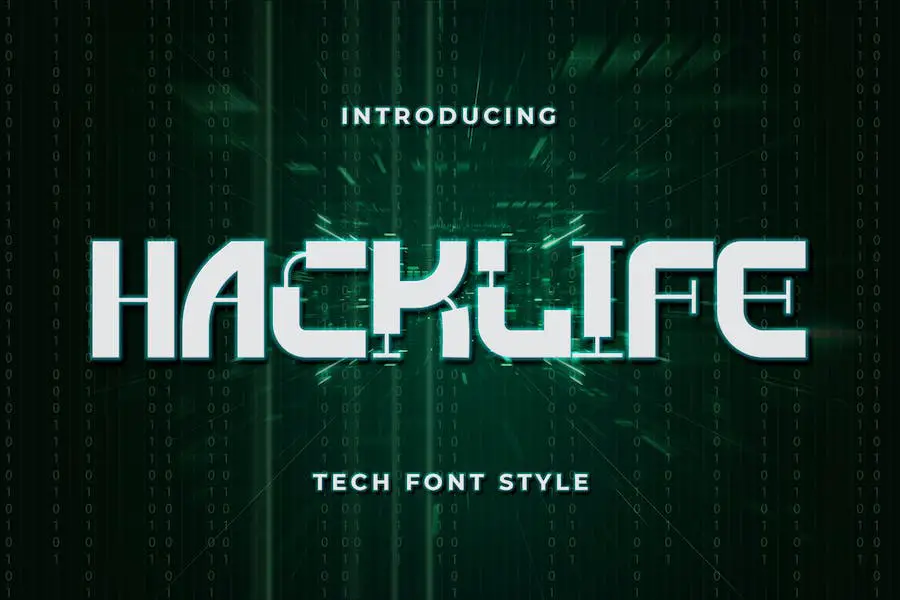
Hacklife 是一种独特而前卫的字体,可以提升您的设计项目。 这种受科技启发的字体具有未来感,非常适合任何科技或计算机主题的设计。 凭借其时尚和现代的外观,Hacklife 将把您的设计提升到一个新的水平。
无论您是在制作网站、徽标,甚至是纹身设计,这种字体都会增添一丝精致和风格。
因此,如果您是一名图形设计师,正在寻找一种字体来增强您的项目,那么 Hacklife 绝对值得考虑。 使用这种未来派字体为您的设计增添额外的优势。
黑客机器人
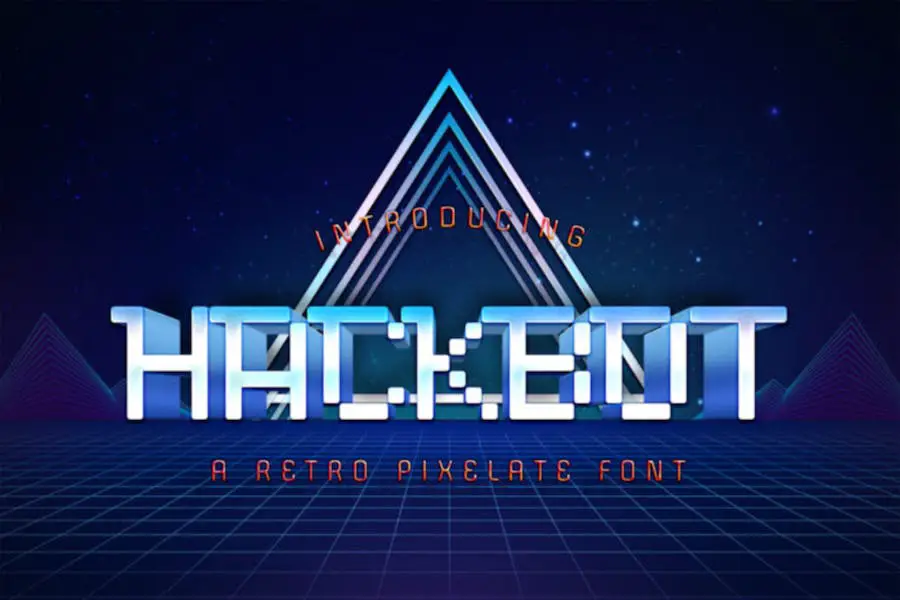
Hackbot 是一种复古风格的字体,可为您的设计增添一丝怀旧气息。 凭借其独特、有趣的字母和复古的感觉,它可以让你回到旧时代。
这种字体采用无衬线书写风格,但具有复古设计风格,使其真正成为独一无二的字体。 无论您是要推广游戏、创建报价单还是进行复古设计,Hackbot 都能完美满足您的所有需求。
Hackbot 的魅力在于字母之间的间隙,这赋予它真正的复古氛围。 这是一种脱颖而出的字体,捕捉了过去的精髓,同时仍然具有视觉吸引力和吸引力。
每封信都经过精心制作,为您的项目带来奇思妙想和有趣的感觉,使它们真正迷人。
Hackbot 是一种多功能字体,可用于多种应用程序,非常适合游戏开发人员和图形设计师。
无论您是想创建引人注目的海报、设计令人难忘的徽标,还是为社交媒体帖子添加复古风格,这款字体都能满足您的需求。 是时候释放您的创造力并让 Hackbot 来说话了。
格斗王
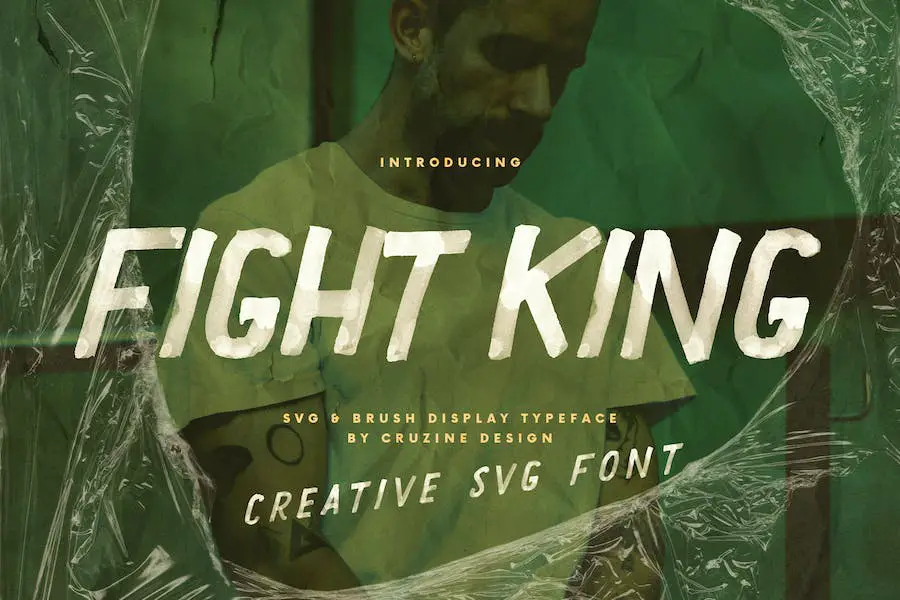
Fight King 是一种独特的手写黑客字体,可为您的项目带来画笔、粗糙或垃圾风格。 这款无衬线显示字体采用大胆的水彩标记设计,非常适合为任何设计增添都市艺术气息。
无论您是在从事垃圾摇滚风格的项目,还是想让您的设计具有前卫的外观,Fight King 都是适合您的字体。 其手工制作的感觉和强烈、大胆的笔触使其成为任何创意活动的杰出选择。
因此,如果您正在寻找一种多功能且引人注目的字体来让您的设计流行起来,请尝试一下《Fight King》。 它一定会给您的项目带来额外的风格和个性!
流畅的线条
隆重推出 Flowing Lines,这是一种手写黑客字体,可为您的项目添加画笔、粗糙或垃圾风格。 这种无衬线显示字体非常适合创建大胆且艺术的外观,特别是对于垃圾、城市或艺术项目。
凭借其大胆的标记风格笔触,Flowing Lines 为您的设计带来独特而前卫的氛围。
这种黑客字体用途广泛,可用于各种项目,从海报到徽标以及介于两者之间的所有内容。 其流畅的线条和手写的外观为任何设计增添了一丝真实性和创造力。
无论您正在从事复古风格的项目,还是希望为您的设计增添一丝叛逆气息,Flowing Lines 都能满足您的需求。
这种字体的画笔风格赋予它原始和有机的质感,使其从其他字体中脱颖而出。 它为您的设计增添了手工品质感,就好像每个字母都是精心手绘的。
Flowing Lines 的粗糙边缘和垃圾摇滚氛围为任何项目带来都市酷感,使其成为那些寻求非传统和叛逆美学的人的首选字体。
Flowing Lines 凭借其大胆的标记笔触,确保您的信息被清晰地看到和听到。 其强烈而自信的外观引人注目,非常适合在设计中使用标题或引人注目的文字。
糖
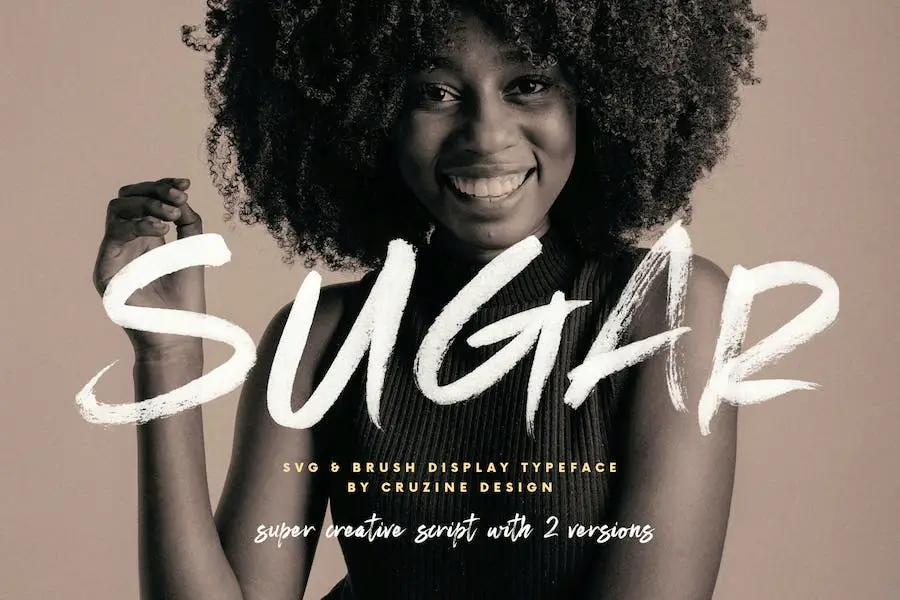
Sugar 是一种独特且多功能的字体,它将把您的设计项目提升到一个新的水平。 凭借其笔刷、粗糙或垃圾风格的脚本,它为任何作品增添了有机和手工制作的触感。
无论您是从事垃圾、城市还是艺术项目,这种手写黑客字体都是完美的选择。
Sugar 的独特之处在于它的笔刷起源,为您的设计带来原始和艺术的外观。 这就像使用真正的画笔来创建版式,但具有数字字体的便利性和精确性。
这种字体非常适合为您的设计添加质感和个性。 其粗犷和垃圾摇滚风格营造出一种前卫感和都市氛围,非常适合时尚、音乐或街头风格的项目。 它真正抓住了另类和叛逆的精神。
黑客
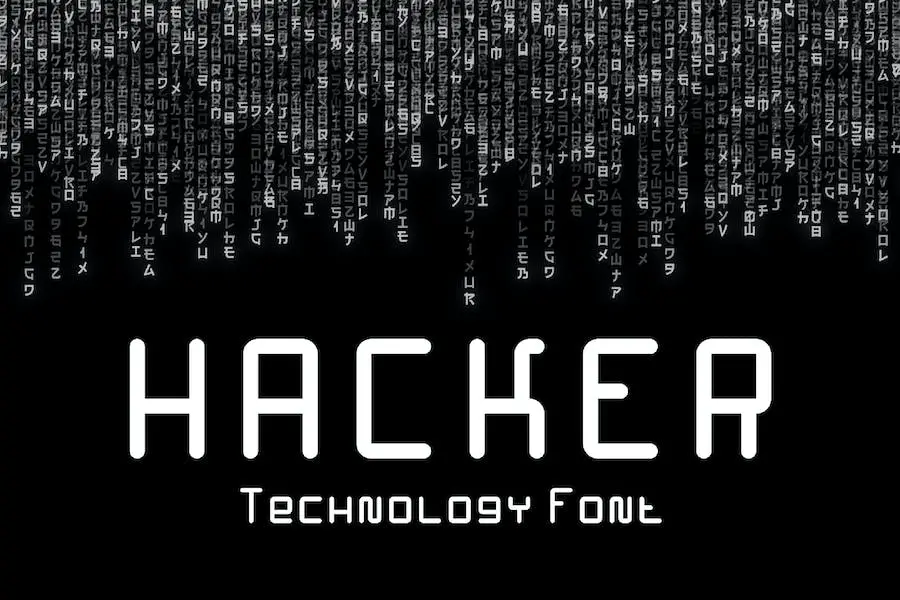
Hacker 是一款令人难以置信的圆形显示字体,散发着明显的复古魅力,让人想起 20 世纪 80 年代。 它毫不费力地抓住了改变世界的计算机革命的本质。
凭借其诱人而大胆的美学,《黑客》绝对是一种视觉享受。 其独特的吸引力使其非常适合各种项目,特别是与网络、安全、互联网、新技术、通信、编码、数据、电子、数学、网络、商业等相关的项目。
这种字体带有一种有趣的熟悉感,仿佛在低声诉说着过去的故事,同时又毫不费力地融入了现代设计景观。 其平滑的曲线和鲜明的特征使其成为任何需要怀旧气息的项目的完美选择。
无论您是创建网站、设计徽标还是制作海报,Hacker 都能增添真实感和个性感。 它毫不费力地捕捉了数字世界的本质及其对创新的不懈追求。
黑客的多功能性是无止境的。 它可以无缝适应任何环境,毫不费力地增强整体设计。 从时尚现代到古怪俏皮,这种字体可以做到这一切。
因此,潜入 Hacker 字体的世界,发挥您的创造力。 拥抱复古魅力,看着您的设计带着优雅和魅力变得栩栩如生。
黑客刷
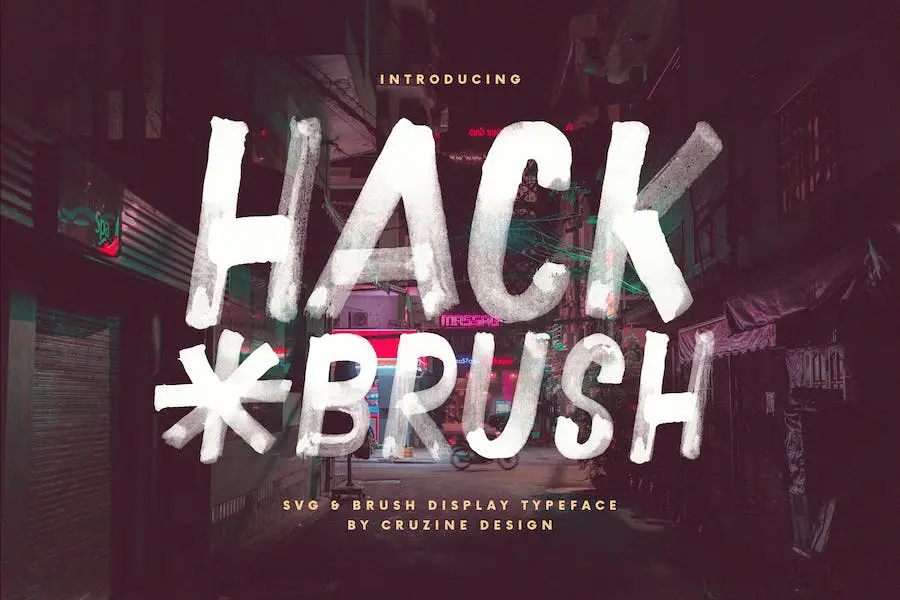
Hack Brush 是一款令人惊叹的手写字体,可为任何设计项目增添一丝大胆和创造力。 这种无衬线字体具有笔刷、粗糙和垃圾风格,非常适合创造独特的都市美感。
该字体采用大胆的水彩笔设计,赋予其艺术感和表现力。
无论您是在创作垃圾摇滚风格的艺术品、城市主题的设计,还是只是想为您的项目添加一点创意,Hack Brush 都是理想的选择。 其手写风格为任何设计增添了个性化和真实的感觉,使其在人群中脱颖而出。
Hack Brush 以其大胆的水彩笔笔触为您的设计带来动感和活力的氛围。 它立即吸引注意力并增添动感和兴奋感。
该字体用途广泛,适用于大标题和正文,让您可以尝试和创建视觉上引人入胜的布局。
Kavure fet Hack
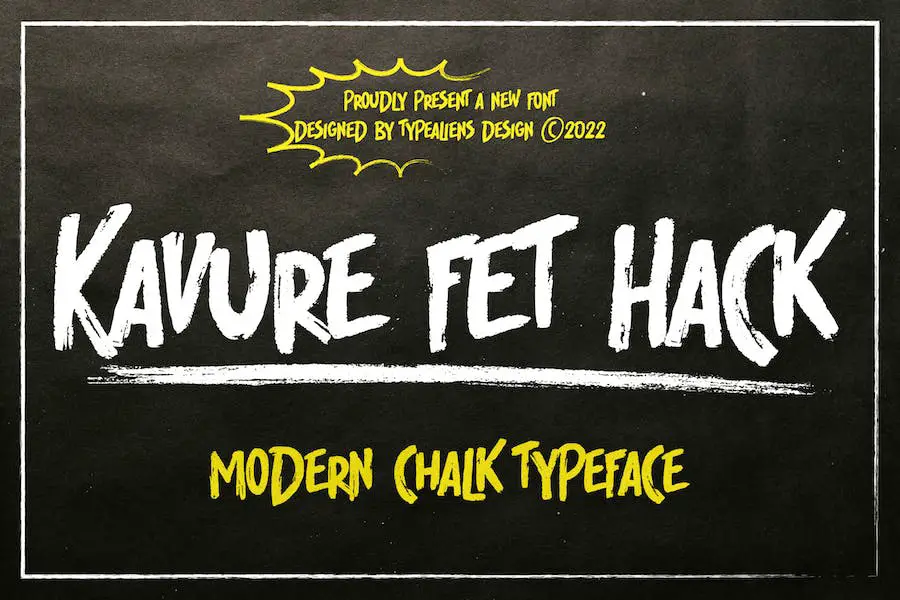
Kavure fet Hack 是一种休闲字体,可为您的设计增添俏皮感。 凭借其独特的粉笔状纹理,它非常适合创造现代轻松的设计。
无论您是在从事饮料产品、零食或咖啡馆的品牌项目,还是在创建社交媒体或产品设计,这种字体都会添加有趣且引人注目的元素。
它的多功能性使其成为想要为项目赋予现代轻松氛围的设计师的绝佳选择。 因此,如果您正在寻找一种能为您的设计带来有趣和休闲感觉的字体,Kavure fet Hack 是完美的选择。
网络
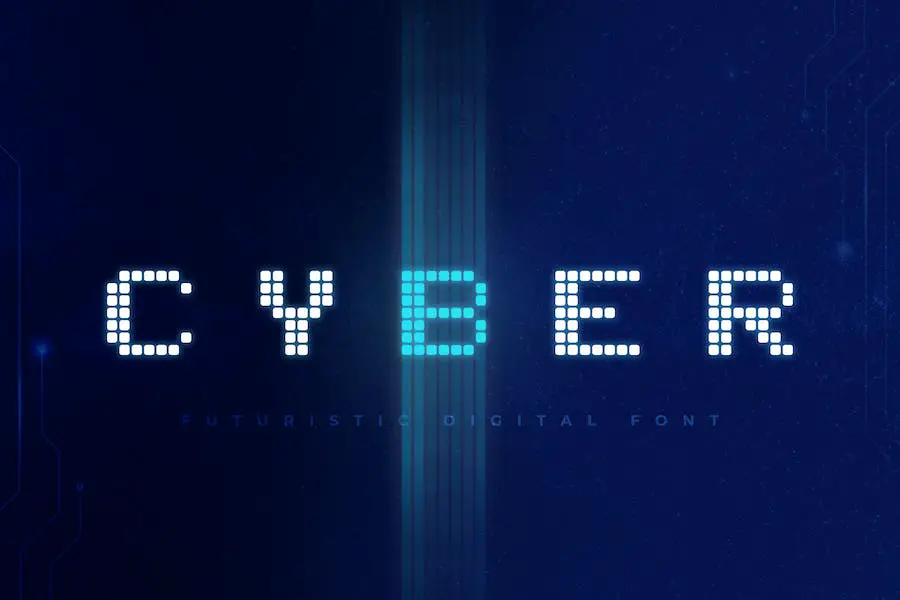
对于那些寻求一些额外的东西来增强他们的项目的图形设计师来说,Cyber是一种很棒的字体。 它非常适合与技术、科幻和科学相关的任何事物,使其成为未来设计的完美选择。
无论您是在创建科幻海报、传单、网站标题还是高科技徽标,这种字体都会将您的工作提升到一个新的水平。
借助 Cyber,您可以为您的设计带来动态和未来感。 其时尚现代的外观为任何项目增添了一丝精致感。 锋利的边缘和简洁的线条赋予其高科技氛围,非常适合捕捉数字世界的精髓。
Cyber 的突出特点之一是它的多功能性。 它可以轻松地跨不同的媒介和平台工作,使您能够创建有凝聚力的品牌和设计元素。
无论您是处理印刷材料还是数字图形,这种字体都能无缝适应任何环境。
阿尔法拉什
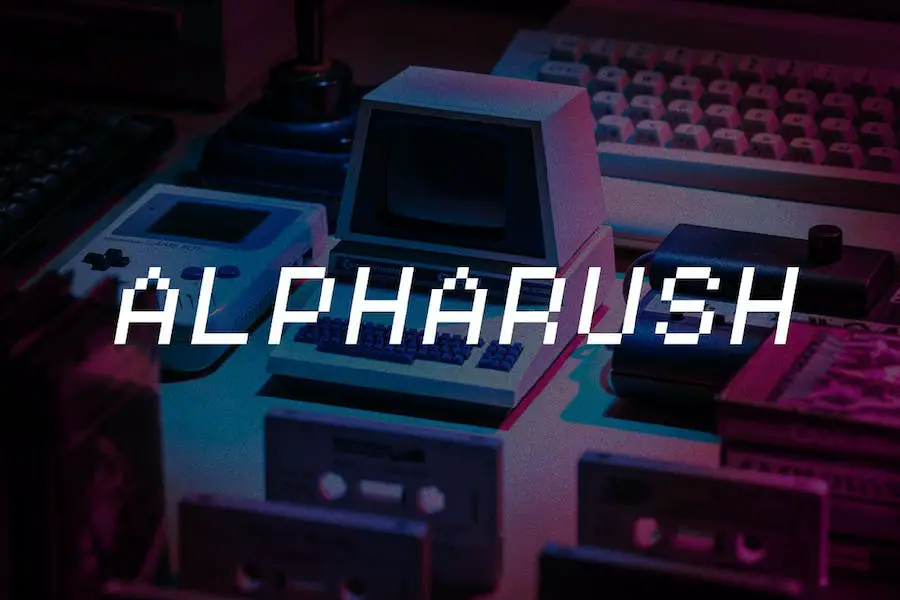
Alpharush 是一款复古 hack 字体,可为任何设计项目带来怀旧的 80 年代感觉。 凭借其像素化和 8 位风格,它是像素艺术和 8 位游戏的完美选择。
无论您是在制作徽标、网站还是任何其他设计项目,这种字体都会增添一丝怀旧和复古魅力。
Alpharush 精心打造,注重细节,以其复古位图设计捕捉 80 年代的精髓。 它的像素化字母和清晰的边缘向过去的经典电子游戏致敬,唤起了那些从小玩这些游戏的人的怀旧之情。
这种字体的多功能性使其适合各种设计项目。 从海报和传单到社交媒体图形和品牌,Alpharush 为您的作品增添了独特且引人注目的元素。
其大胆而独特的特征彰显个性并吸引注意力,确保您的设计脱颖而出。
无论您是图形设计师还是希望提升项目的业余爱好者,Alpharush 都是必备字体。 其复古和怀旧的氛围为您的设计带来了过去的气息,使它们在视觉上具有吸引力和吸引力。
使用 Alpharush 为您的项目赋予 80 年代的魅力,并以其独特的风格给您的观众留下深刻的印象。
最佳免费黑客字体
希望为您的设计项目添加一些时尚现代的字体? 我们精心挑选的 15 种最佳黑客字体就是您的最佳选择。 这些免费字体一定会让您的设计更上一层楼并激发创造力。 不要错过,现在就来看看吧!
被黑
HACKED 是一种非凡的字体,可以极大地增强您的项目设计。 凭借其独特而时尚的外观,它非常适合寻求将其工作提升到新水平的平面设计师。 该字体与Canva兼容,让用户使用起来更加方便。
HACKED 的特点包括其时尚而现代的外观,为任何设计增添了一丝精致感。 简洁的线条和鲜明的字符使其易于阅读,同时仍保持原创感。
这种字体用途广泛,可用于从徽标到社交媒体帖子的各种项目。 其大胆和引人注目的性质确保您的设计将脱颖而出。
此外,HACKED 的安装和使用非常简单。 无论您是经验丰富的图形设计师还是刚刚起步,您都可以毫无困难地将这种字体融入到您的项目中。
它与各种软件和平台兼容,确保您可以在任何您喜欢的工作地点使用它。
黑客攻击
Hack Attack 是由 Iconian Fonts 制作的字体,专为寻求提升项目设计的图形设计师而设计。 这种字体提供了时尚和现代的美感,使其成为任何设计工作的绝佳选择。
凭借其广泛的风格和多功能性,Hack Attack 一定会为任何项目增添一丝复杂性。
Hack Attack 的突出特点之一是其广泛的风格选择。 从大胆前卫到优雅精致,这种字体拥有一切。
无论您是在进行徽标、包装还是网页设计,Hack Attack 都提供多种样式可供选择,确保您能够找到最适合您的项目的样式。
Hack Attack 还具有出色的易读性,使其易于阅读和理解。 这对于图形设计师来说尤其重要,因为易读性在有效传达信息方面起着至关重要的作用。
选择最佳的 hack 字体取决于个人喜好和编码项目的具体要求。 考虑字体的易读性、字符区别和整体视觉吸引力等因素。
尝试不同的 hack 字体,看看它们的感觉和外观如何,找到最适合您的编码风格并提高您的工作效率的字体也很有帮助。
结论
总之,我们探索了 15 种最佳黑客字体,图形设计师可以使用它们来增强他们的项目设计。 这些字体不仅为您的设计增添了独特和时尚的触感,而且还传达了现代和前卫的美感。
从经典大胆的风格到时尚简约的风格,每种设计需求都有一种黑客字体。